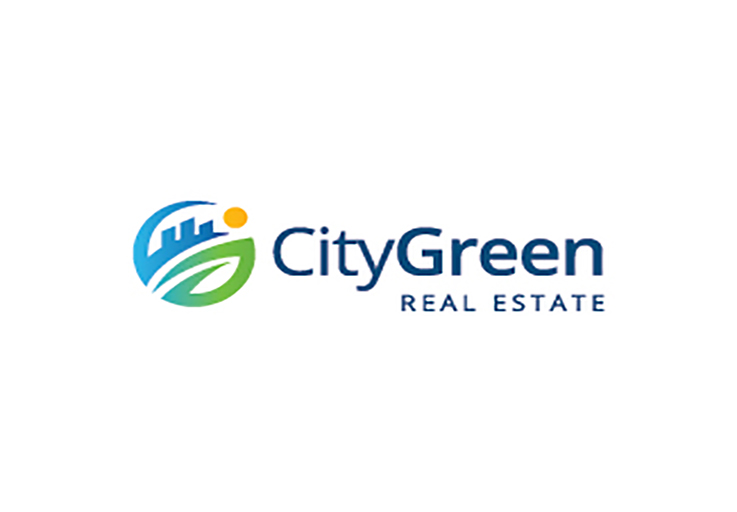
Sử dụng font chữ trong thiết kế logo
Sử dụng font chữ trong thiết kế logo như thế nào đểcho logo của bạn sáng tạo và nổi bật, không bị tách biệt làm mất thẩm mỹ và ý nghĩa logo là rất quan trọng mà đôi khi các nhà thiết kế logo chuyên nghiệp cũng hay mắc phải. Mỗi font chữ cũng có những ý nghĩa riêng của nó, hiểu rõ nó cũng sẽ mang lại những hiệu quả bất ngờ.
Sử dụng font chữ trong thiết kế logo với các kiểu font chữ của đồ hoạ
Ngày nay với rất nhiều font chữ nhưng về cơ bản chúng ta có thể chia làm 3 dạng cơ bản: đó là font không chân, font có chân và font dạng bay bướm. Vì vậy khi thiết kế logo chúng ta sử dụng font chữ như thế nào để logo mang được giá trị tốt nhất .Mỗi font đều mang những ý nghĩa riêng như font không chân với đường nét thẳng, mạch lạc thường mang ý nghĩa hiện đại, sang trọng. Trong khi font có chân thể hiện sự nghiêm trang, lịch sự. Và font dạng bay bướm thể hiện sự phóng khoáng, nên tùy vào trường hợp và hoàn cảnh cụ thể để sử dụng hợp lý.
Sử dụng font chữ trong thiết kế logo cần hoà hợp với hình tượng logo
Sử dụng font chữ trong thiết kế logo cho phù hợp
Logo là một trong những ấn phẩm đồ họa đòi hỏi kỹ thuật cao vì thế sử dụng font chữ trong thiết kế logo cũng cần lựa chọn thật kỹ kiểu dáng và font chữ phù hợp với đường nét hình tượng logo, hoặc có thể thể hiện trên mọi chất liệu, phóng to hoặc thu nhỏ ít nhất 2,5 cm mà không mất đi hoặc thay đổi ý nghĩa của logo. Đối với những thiết kế logo chuyên nghiệp các họa sĩ thiết kế không sử dụng những font chữ có sẵn mà thường sáng tạo ra một font chữ khác cho phù hợp với thiết kế logo đó.
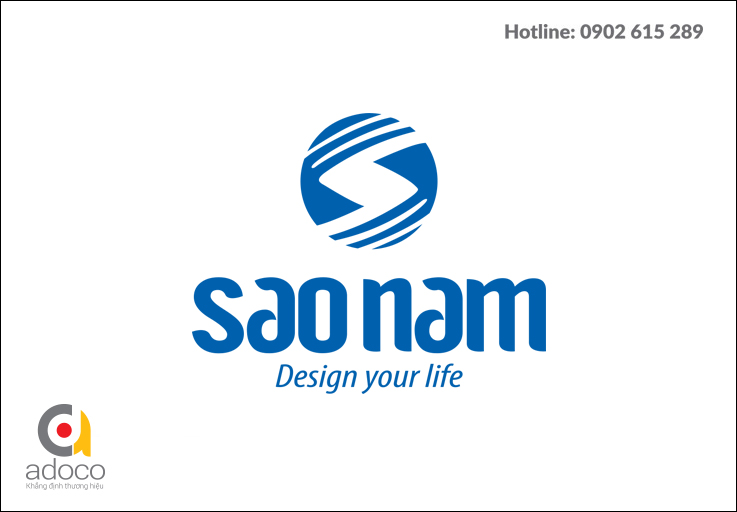
Những font chữ được cách điệu đó thường là những tên thương hiệu ngắn gọn và cách điệu tạo điểm nhấn chứ không phải cách điệu một cách tràn lan. Sự phù hợp của font chữ trong thiết kế logo thường do hình tượng của logo quyết định, nếu hình tượng logo của bạn có đường nét đậm và nhạt, có những góc nhọn thì khi sử dụng font chữ cho logo đó bạn cũng nên sử dụng font chữ có những đường nét tương tự. Nếu logo của bạn là những đường nét khỏe mạnh, hiện đại thì những font chữ không chân có nét tương đồng nên được sử dụng. Trong một thiết kế logo chuyên nghiệp thì tốt nhất chúng ta chỉ nên sử dụng một loại font chữ tránh gây sự rối rắm mất đi hình ảnh ý nghĩa của logo.
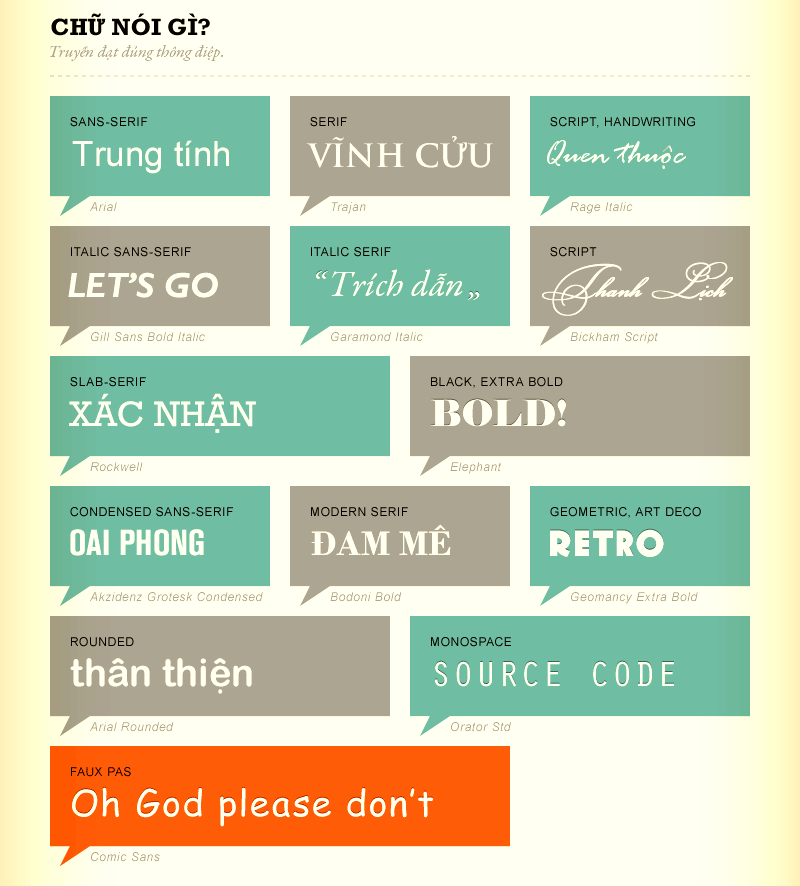
Ý nghĩa một số font chữ